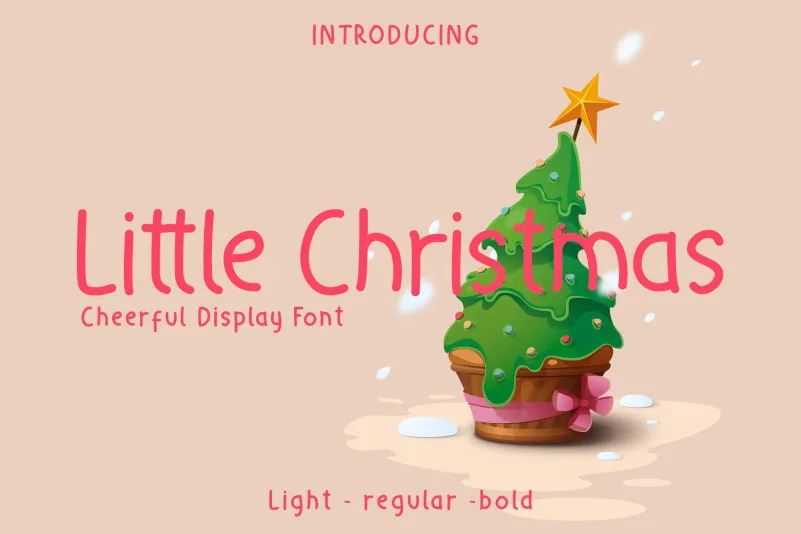
Little Christmas – Cheerful Holiday Font – Fonte Grátis
Little Christmas – Cheerful Holiday Font – Download Grátis
Little Christmas - Cheerful Holiday Font
A Little Christmas – Cheerful Holiday Font é uma tipografia sans serif com traços levemente alegres que se destaca como a escolha perfeita para projetos natalinos e festivos. Conhecida por sua simplicidade moderna, essa fonte traz um toque de felicidade às suas criações gráficas. Perfeita tanto para logomarcas quanto para designs em cartazes e materiais publicitários, a Little Christmas é perfeitamente adaptada ao tema do natal ou qualquer outra celebração festiva da temporada. Seu visual leve e divertido combina de forma ideal com o espírito acolhedor dos tempos de fim do ano, tornando-a uma escolha inteligente para projetos que buscam transmitir alegria e harmonia durante os meses frios de inverno. Com Little Christmas, você pode garantir um design moderno e encantador que deixará seu trabalho de design brilhar ainda mais em sua coleção de recursos gráficos.